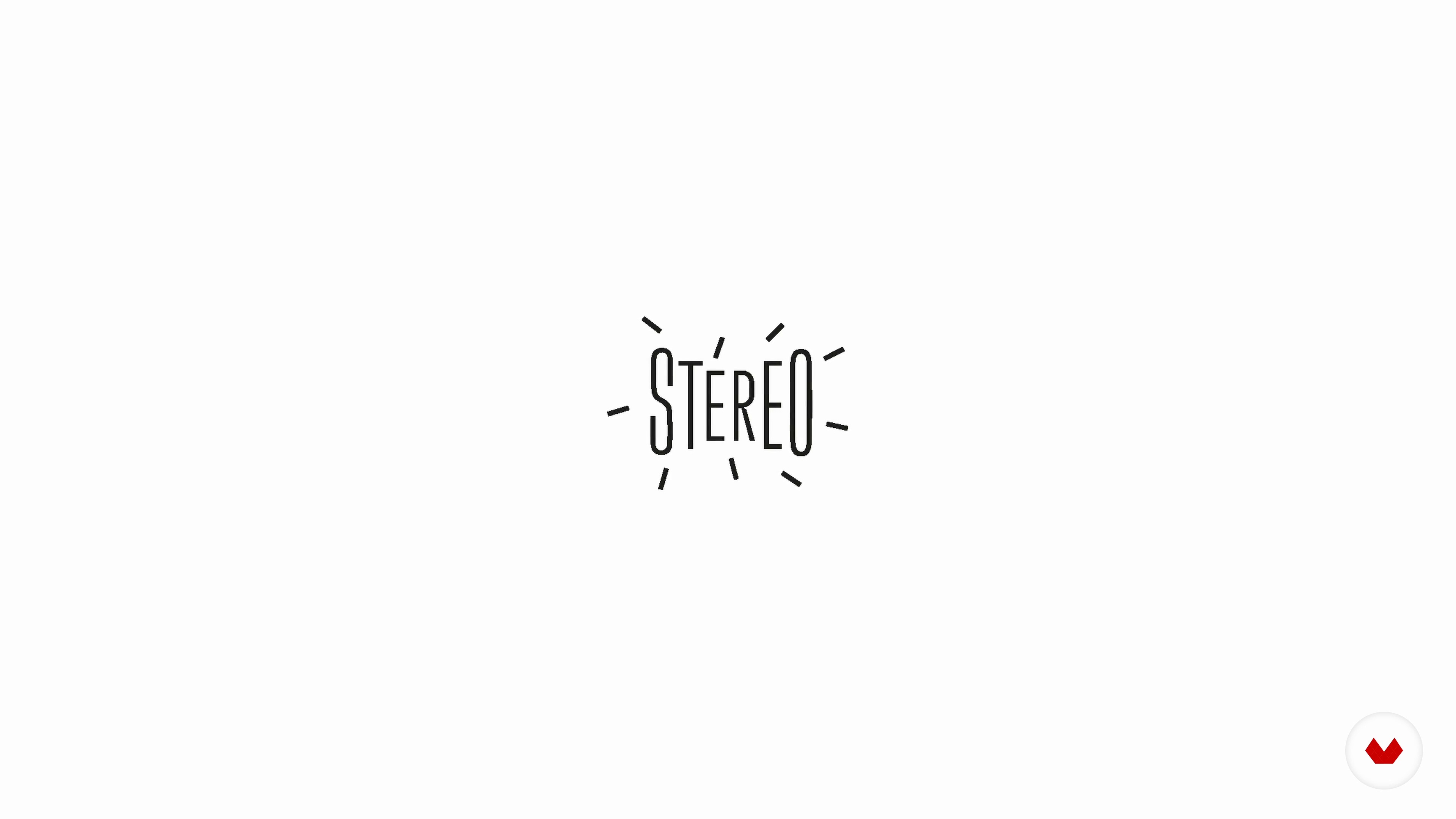
La typographie
“À présent, nous vous montrerons comment associer une typographie à une piste, et nous vous expliquerons comment justifier votre choix dans le cadre de votre projet. ”
Dans cette leçon, Studio Plastac aborde le sujet : La typographie, qui fait partie du cours Domestika en ligne : Création d’une identité visuelle appliquée à un lieu. Réussissez vos projets d’identité visuelle et sublimez un espace de vie en travaillant le logo, la charte graphique et la communication sur les réseaux sociaux.
“ La typographie Dans cette leçon, on verra comment associer une typographie à une piste, et justifier nos choix. On va aborder un domaine qui me passionne, la typographie et son histoire. Il existe beaucoup de classifications typographiques. On a choisi d'en retenir une, assez simplifiée, mais qui a l'avantage d'être utilisée par beaucoup de fonderies modernes. Cette classification est divisée en cinq ensembles, les Serif, les Mécanes, les Sans serif, les Mono et les Script. Commençons par la première sous-famille de cette classification, les Serif. Ici, on a retenu deux typographies, la C...”